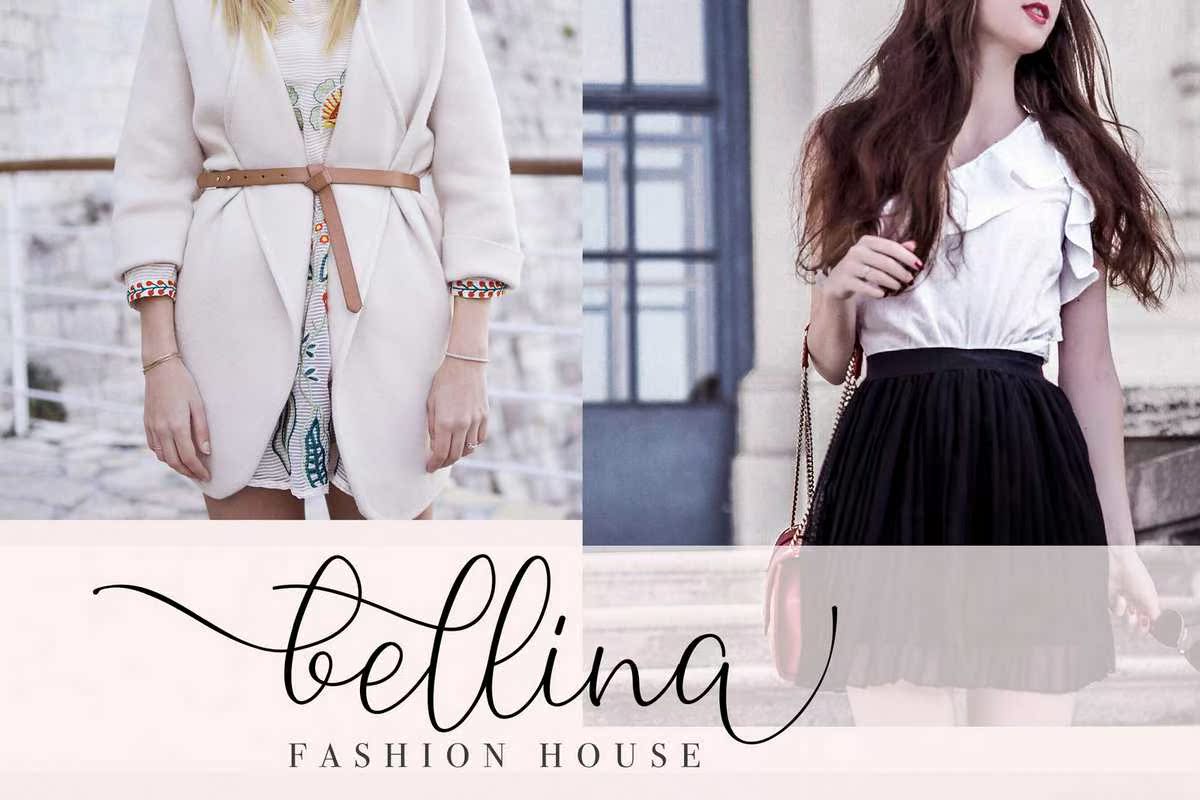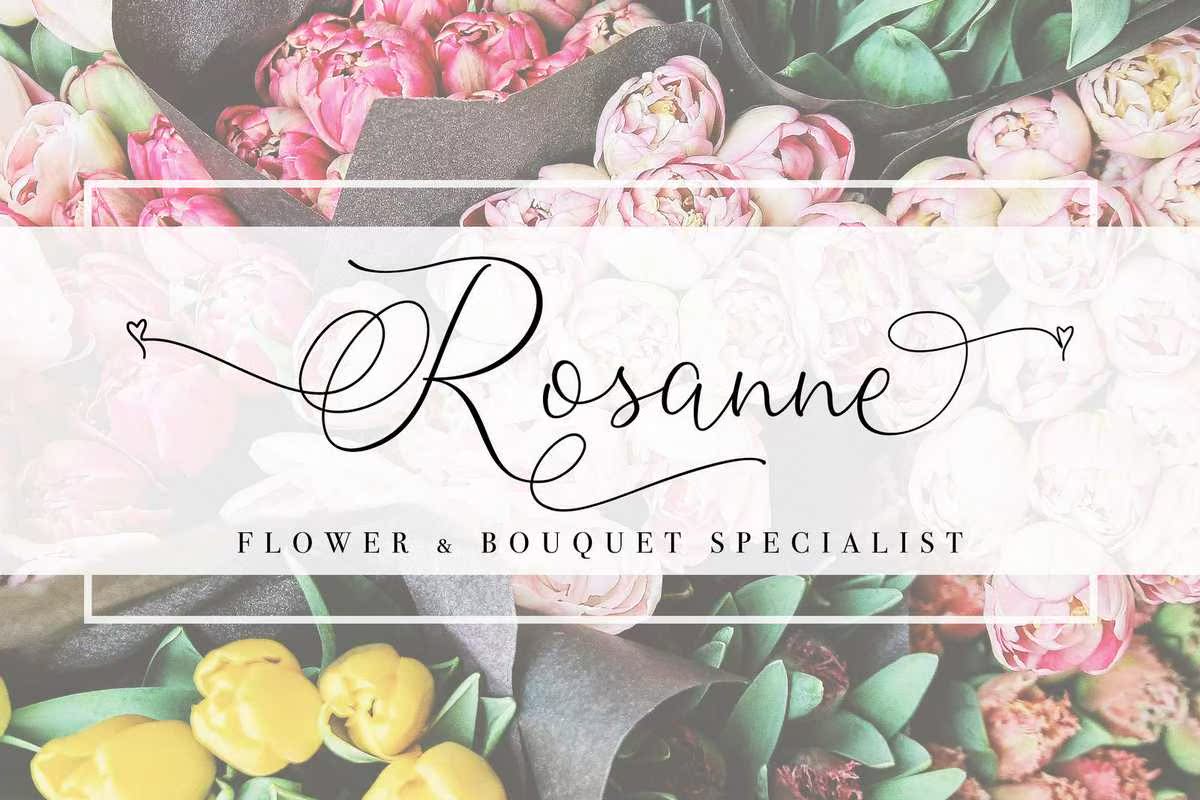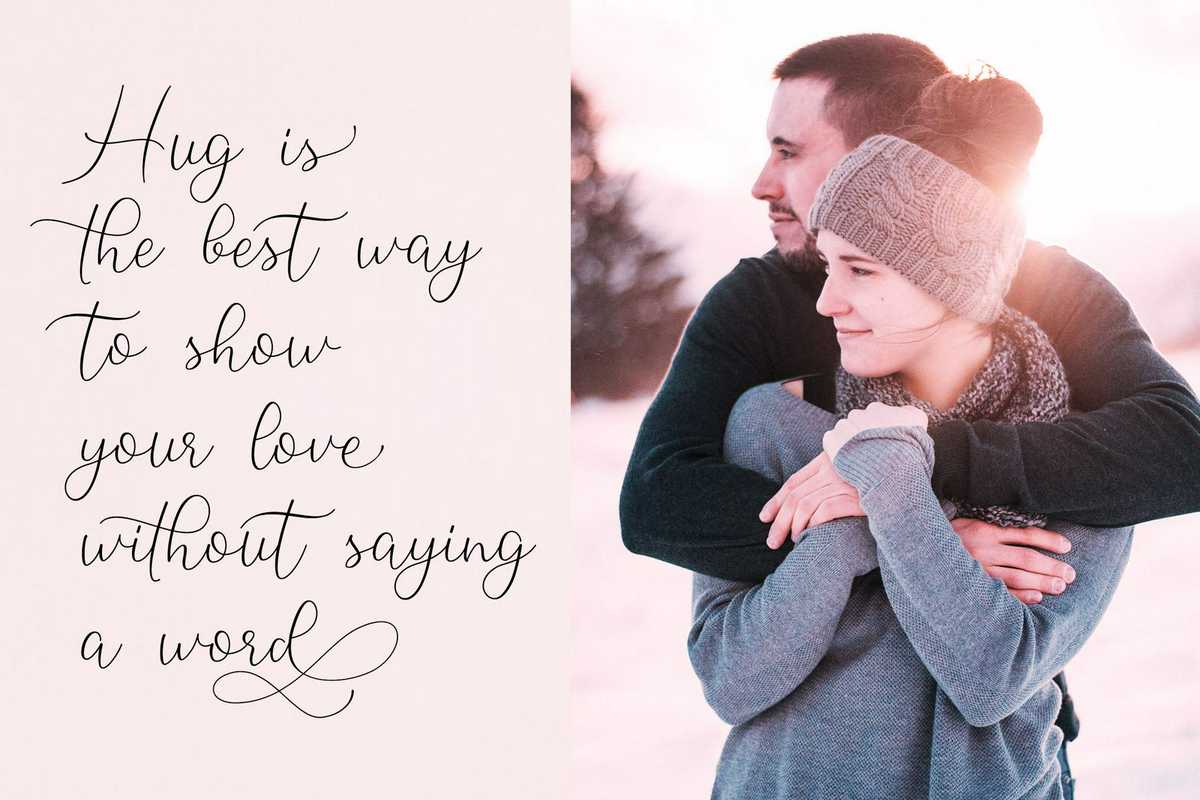
Meilly Neisa TurlyGorgeous和Magical Scripts具有iquiecalligraphic样式。Fally Neisa TurlyGorgeous和Magical Scripts具有iquiecalligraphic样式。Fally Neisa TurlyGorgeous和Magical Scripts具有强大的清洗和装饰性,可即时接触任何项目。Meilly Neisa TurlyGorgeous和Magical Scripts具有iquiecalligraphic样式。Fally Neisa Neisa。